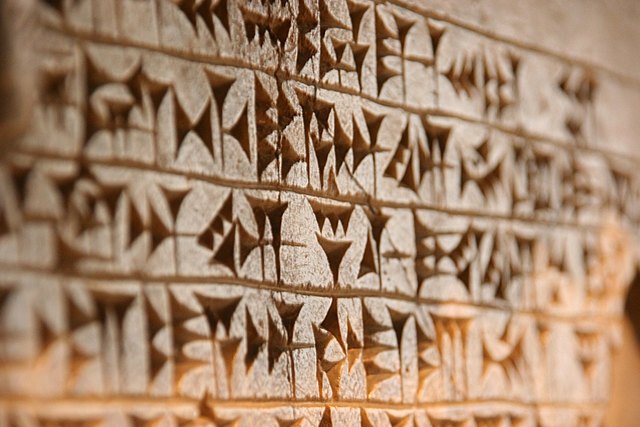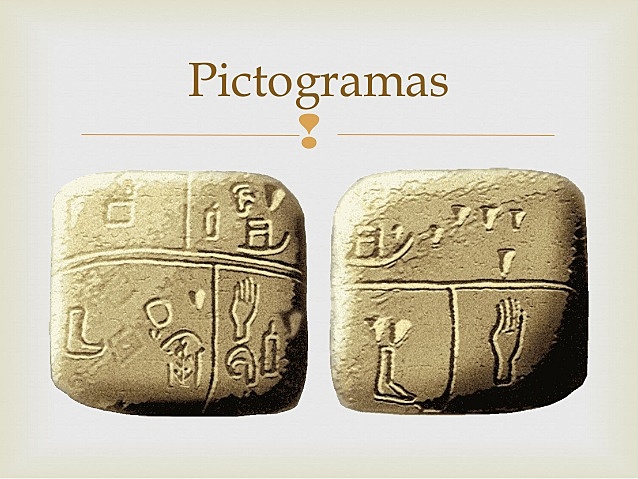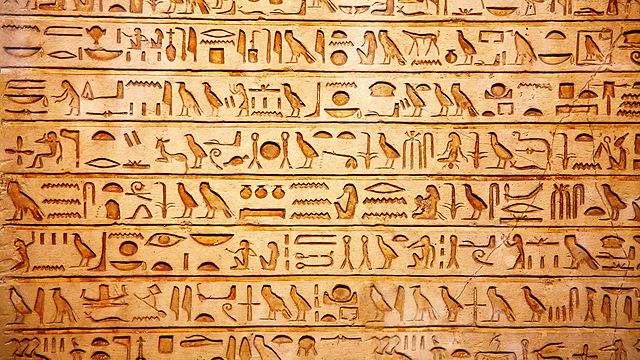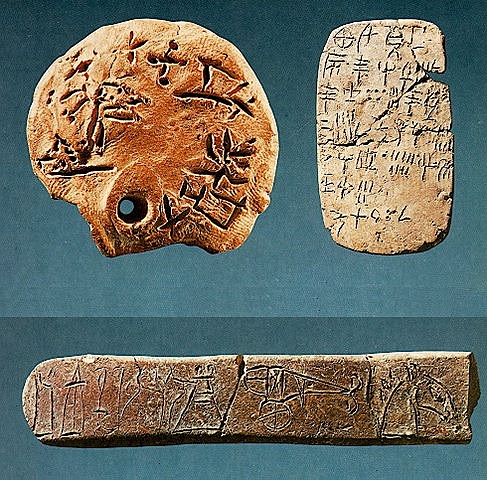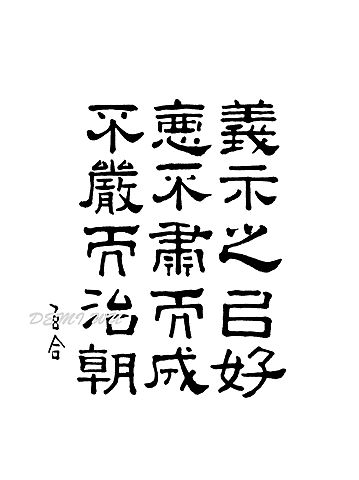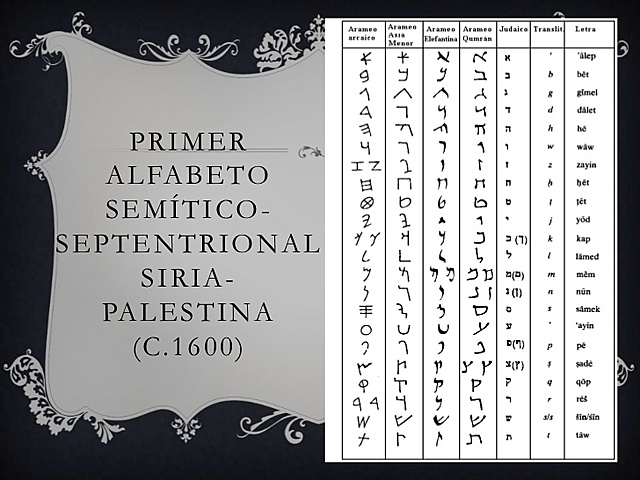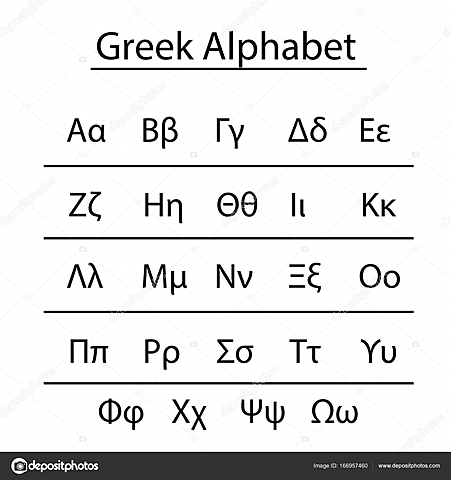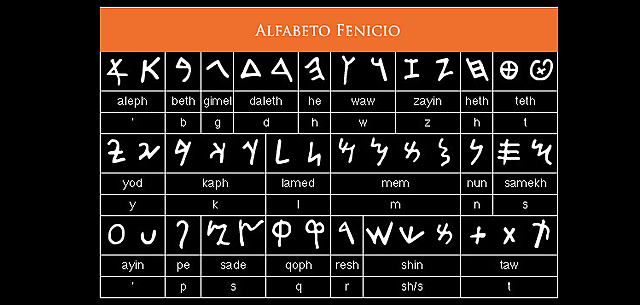
Eran fonogramas escritos en arcilla húmeda, nace, en primer lugar, ante la necesidad de contabilizar bienes y transacciones, es decir, su origen tenía una finalidad contable
Eran signos icónicos figurativos y realistas que representan de forma dibujada más o menos esquemática objetos.
En la pictografía las escenas tenían un fin causativo -
Conforman la escritura de algunas antiguas civilizaciones, como la maya o los hititas que representa las palabras mediante figuras o símbolos como ideogramas, logogramas o pictogramas
También llamado Jeroglíficos Cretense fue un sistema de escritura en Creta posiblemente en 1900 a.C a 1650 a.C
Es tan poco el material que se conserva y su contenido es tan breve y recurrente que es prácticamente imposible. Se desconoce, por tanto, la lengua que se esconde detrás de esta escritura. -
Por lo general se asiente que es el primer alfabeto conocido. Surgió en lo que hoy es Siria y Palestina entre el 1700 a.C. y el 1500 a.C. Aparece como una amalgama de los símbolos cuneiformes y jeroglíficos
Los caracteres chinos, a veces llamados sinogramas, son un sistema de escritura de tipo logográfico y silábico desarrollado por los chinos han, usados desdee 1200 a.C hasta la actualidad
El alfabeto fenicio es un antiguo alfabeto consonántico, es técnicamente una escritura abyad es decir formada por símbolos , y no es una escritura pictográfica (de signo icónico).
El fenicio se convirtió en uno de los sistemas de escritura más utilizados al ser difundido por los mercaderes fenicios a lo largo del mundo mediterráneo -
El alfabeto griego es un alfabeto de veinticuatro letras utilizado para escribir la lengua griega. Desarrollado alrededor del siglo IX a. C. a partir del alfabeto consonántico fenicio
los griegos adoptaron el primer alfabeto completo de la historia, entendiéndolo como la escritura que expresa los sonidos individuales del idioma, es decir que prácticamente a cada vocal y cada consonante corresponde un símbolo distinto. -
El alfabeto arameo es un alfabeto abyad (de simbolos) diseñado para escribir idioma arameo El uso del arameo como una lengua franca a través del Oriente Medio desde el siglo VIII a. C. llevó a la adopción gradual del alfabeto arameo para escribir hebreo.